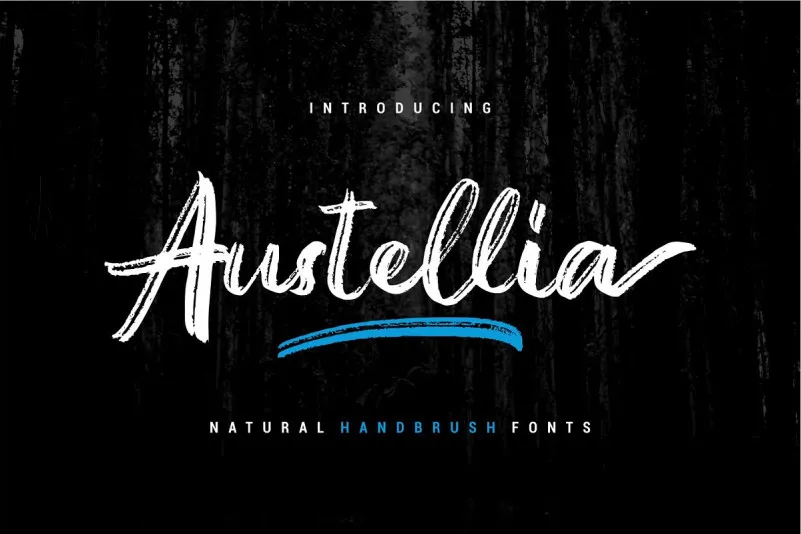
Austellia Handbrush Font – Fonte Grátis
Austellia Handbrush Font
Esta é uma fonte script chamada Austellia Handbrush Font, criada pelo designer 0001themes. Ela traz um estilo de escrita à mão com toques de esponja e influências de traços autênticos, parecendo uma passagem pelo mundo da arte gráfica. Ideal para designers desbravadores que buscam algo novo e autêntico para adicionar a seus projetos. Esta fonte foi feita usando verdadeiras ferramentas à mão, resultando em uma opção de OpenType com ligaturas únicas. Ela adicionará um valor estético incrível aos seus designs. Você também terá acesso às fontes Austellia e ao Swash, permitindo que você conjure a magia do design artístico. Que tal embarcar nesta viagem única?